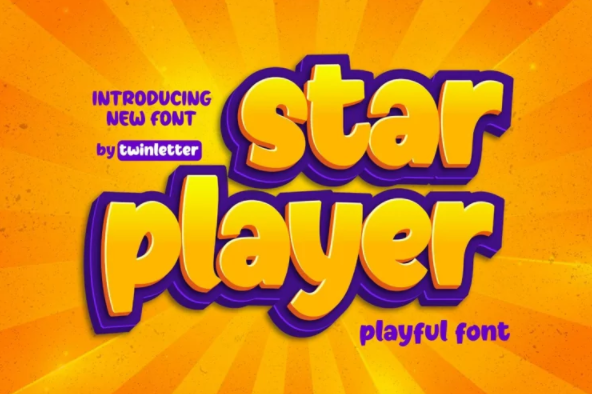
[Fontbundles] Star Player Font (2021)
Шрифт Star Player был создан с учетом мощной и смелой идеи.
Благодаря использованию этого шрифта ваш проект мгновенно станет уникальным, великолепным, элегантным и сильным.
Благодаря своей элегантной и гибкой форме, этот шрифт идеально подходит для использования в качестве заголовка или текста предложения; все будет выглядеть красиво и аккуратно, и, конечно же, останется четким и сильным.
Этот шрифт идеально подходит для игр, спортивных мероприятий, брендинга, баннеров, плакатов, названий фильмов, книг, цитат, логотипов и многого другого.
Конечно, ваши различные дизайнерские проекты будут идеальными и необычными, если вы будете использовать этот шрифт, потому что этот шрифт оснащен комплиментарным семейством шрифтов, как для заголовков, так и для подзаголовков и текста предложений.